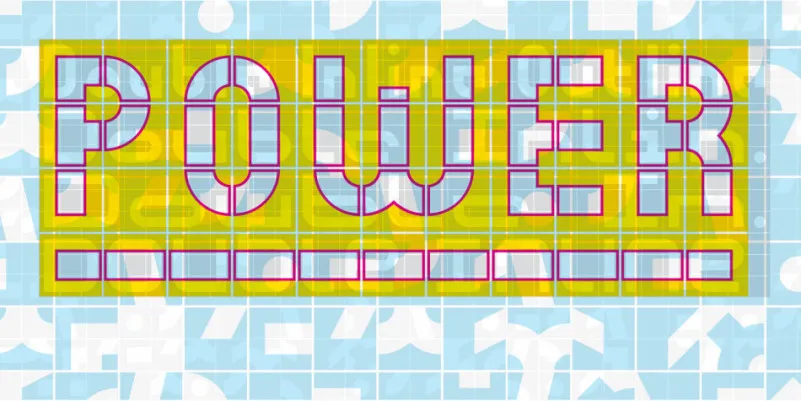
Introduzimos a você uma nova família de fontes de display. Introduza a Nepos Font Family! Esta família foi projetada pela Astype e agora está disponível para compartilhamento. A Nepos é um kit modular experimental composto por várias tipografias prontas para uso, além de uma série especial de fonts BUILD para construção própria letras e ornamentos. Estas fonts BUILD podem ser usadas em camadas com cores diferentes e sobrepostas para efeitos especiais. Este é mais que apenas uma fonte; é uma ferramenta de design flexível, permitindo que designers criem textos únicos e personalizados sem limitações. Se você gosta de explorar fronteiras inexploradas no mundo da tipografia, então a Nepos Font Family certamente será algo que desejará ter em sua biblioteca.